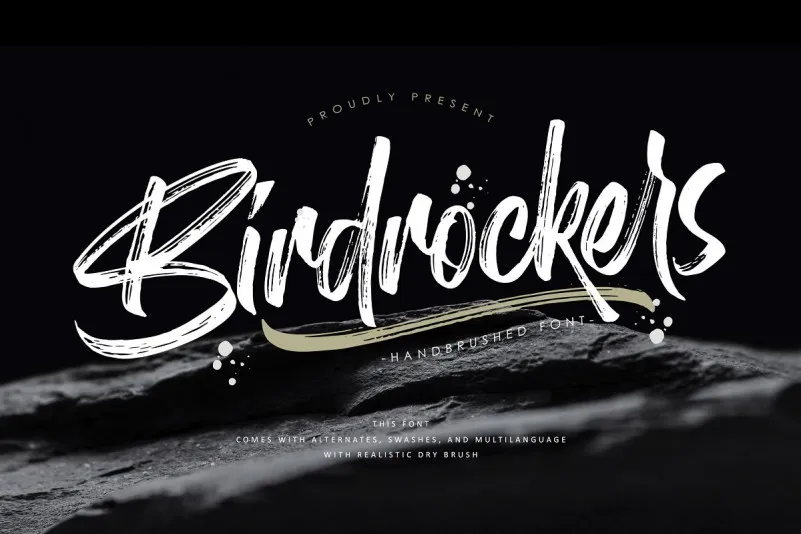
Birdrockers Brush Font
Presentamos uma nova opção no mundo das fuentes script para aqueles que buscam uma solução perfeita para projetos criativos. Introduzimos a Birdrockers Brush Font, uma moderna e realista fonte de pincelagem, perfeitamente adaptada ao estilo do Design Gráfico de Pincel. Inspirado em técnicas tradicionais de pintura com pincéis, esta fonte oferece um toque autêntico que transforma qualquer projeto em algo único e autoral. A Birdrockers Brush Font é ideal para quem procura uma fonte versátil, adequada tanto para criação de logotipos quanto para trabalhos mais elaborados como posteres ou letras digitais. Suas características incluem alternativas de letra, ligaduras e extras de swashes que proporcionam um toque moderno à escrita. Além disso, a fonte vem com textura brand nova e estilo, tornando-a uma escolha perfeita para aqueles que desejam criar letras manuscritas ou letrinhas personalizadas. Com a Birdrockers Brush Font de Hamilton, você terá todas as ferramentas necessárias para explorar e experimentar o mundo da design gráfico em sua totalidade. Ideal tanto para designers digitais quanto para artistas de logotipos e artes de signos, esta fonte oferece uma variedade infinita de possibilidades ao seu projeto. Não hesite em incorporar a Birdrockers Brush Font à sua arsenal de ferramentas, ela certamente fará sua arte um pouco mais realista e autêntica.